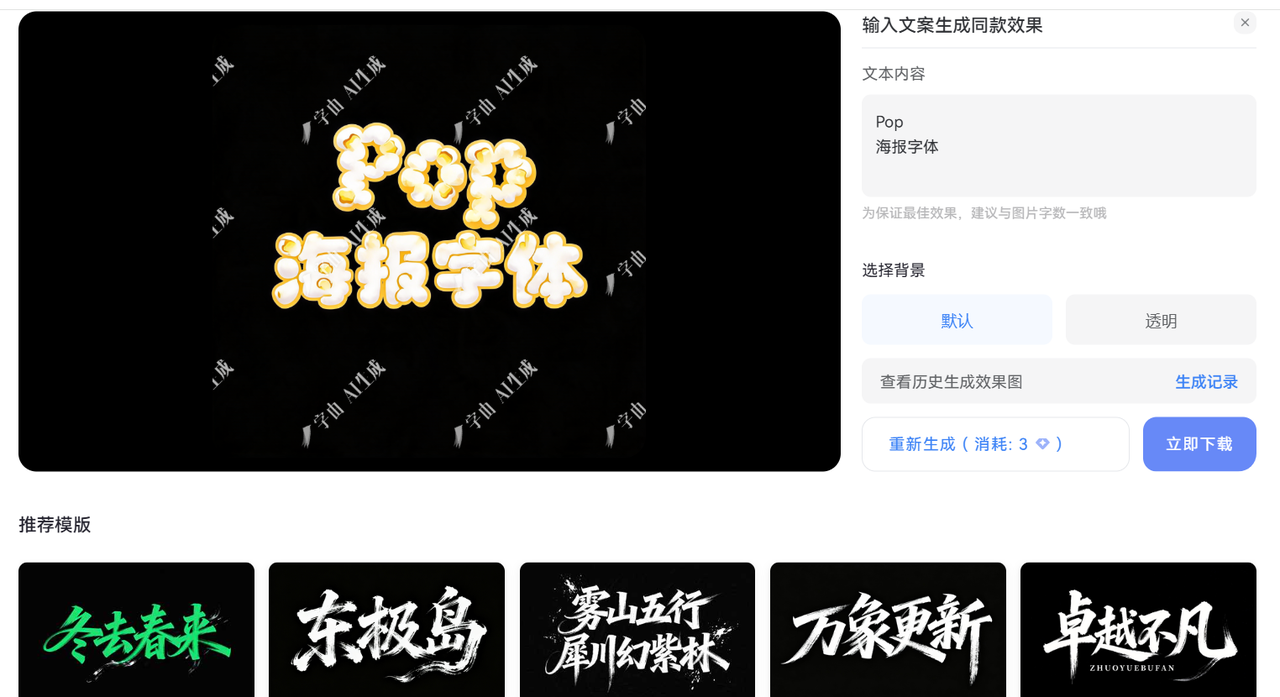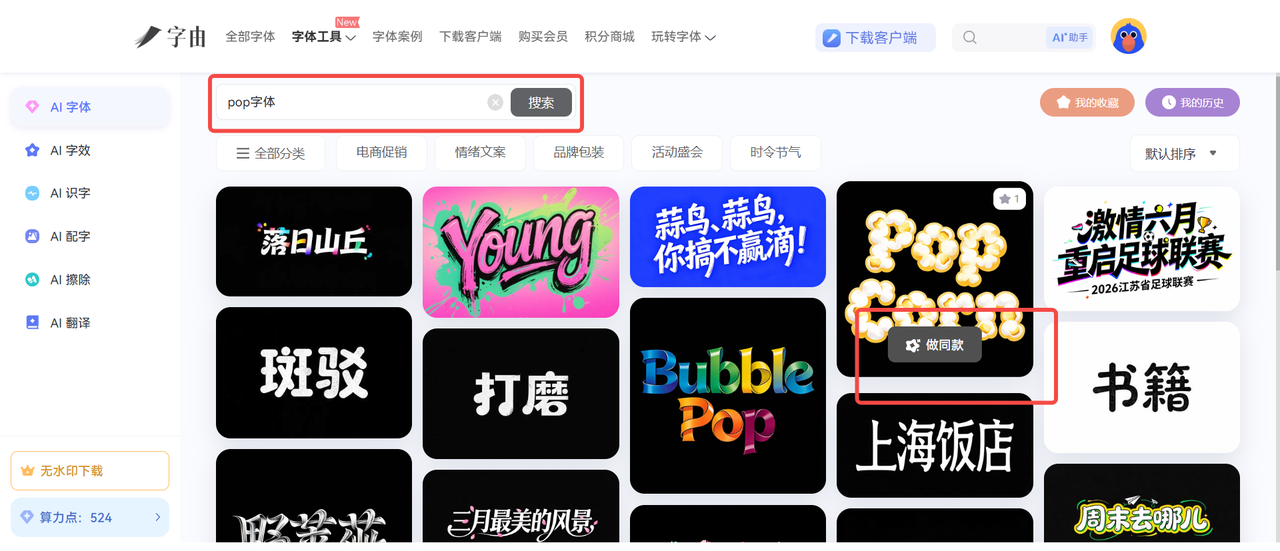
pop海报字体下载推荐:5个实用字体下载网站分享
当我们想制作一张海报时,无论是门店促销海报、活动宣传页,还是社交媒体推广图片,字体的使用往往会直接影响到最终的视觉呈现效果。而很多朋友在寻找 pop 海报字体时,常常会遇到字体风格不匹配、授权范围不明确、下载后难以管理使用等问题。不用担心,今天本文已经整理好了 5 款适合下载 pop 海报字体的字体网站,接下来,我将为你详细介绍这 5 个网站各自的功能特点,以及适用场景,一起来看看吧!
1、字由:可自定义 pop 海报字体设计效果
首先推荐给大家的是国内的专业字体平台【字由】。在 pop 海报设计的场景中,它不仅提供精致的字体素材,还能结合字体管理、字体应用以及商业授权服务,帮助我们更方便地完成从寻找字体到应用字体的完整流程。当然,如果你感觉市面上并没有太理想的 pop 字体设计效果,字由同样还支持你来自定义,并为你提供了简单的操作方式,一起来看吧!
2、Google Fonts
Google Fonts 虽然并不是专门针对POP海报设计打造的平台,但站内部分字体具有较强的视觉表现力,十分适合用于活动海报设计以及网页宣传素材。
在字体查找的过程中,Google Fonts 的分类方式比较清晰,我们可以按照字体类型、粗细、语言支持等条件进行筛选。如果要制作 pop 字体海报,可以重点关注具有明显笔画变化、较大字面空间或者个性化风格的字体。对于要制作英文海报、国际化活动页面或者需要搭配英文标题设计场景的设计师来说,Google Fonts 是一个比较方便的选择。
3、Font Squirrel
如果想在 Font Squirrel 中下载 pop 海报字体,我们可以选择一些具有复古风格、手绘效果或者粗体设计特点的字体。相比一些只提供字体文件下载的平台,Font Squirrel 会更注重字体版权信息展示,这一点对于要进行商用的设计师来说比较重要。不过,该网站主要面向英文字体资源,如果需要中文 pop 字体,选择范围会相对有限。
4、DaFont
DaFont 拥有大量不同风格的字体资源,网站中的字体类型十分丰富,从手写字体、漫画字体、再到装饰字体、复古字体等,都可以在 DaFont 站内找到。
但相对而言,它比较适合寻找具有设计感的标题字体。例如制作年轻化活动海报、娱乐宣传图片或者社交媒体内容时,可以来 DaFont 站内寻找能增强视觉效果的字体设计。如果你希望寻找一些区别于常规商业字体的 pop 海报风格字体,可以把 DaFont 作为一个补充选择。
5、FontSpace
FontSpace 提供了大量免费的字体下载资源,而且会在页面中将字体效果直观地展现出来,我们无需进入详情页,也能快速预览到具体的字体设计效果。
对于 pop 海报设计而言,FontSpace 中的一些创意字体比较适合用于标题、活动主题文字以及装饰性文字设计,我们可以使用关键词,比如 display、handwriting 等来快速筛选到符合视觉需求的字体。但和其他海外字体网站一样,使用 FontSpace 站内的字体前仍然需要确认字体授权范围,特别是在商业项目中使用时,需要仔细查看相关说明。